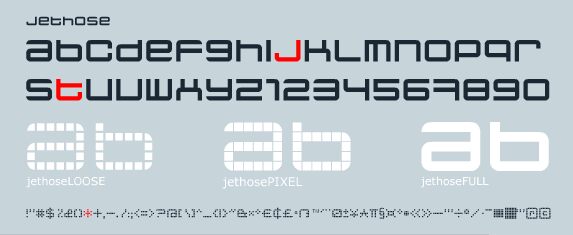
Jethose Full ist eine kostenlose, futuristische Display-Schrift mit einem markanten modularen Charakter. Sie besteht aus weichen, quadratischen Kurven und konsistenten Strichstärken und erinnert an Buchstaben, die aus glänzendem Kunststoff geformt oder als Leuchtröhren gestaltet sind. Die großzügigen Punzen und der straffe Rhythmus verleihen ihr eine klare, technisch präzise Anmutung, die schnell lesbar ist und gleichzeitig unverkennbar digital wirkt.
Mit Jethose Full verleihst du Sci-Fi-Postern, Logos für Tech-Startups, Spieletiteln, Covern für elektronische Musik und Veranstaltungsflyern einen schlanken, futuristischen Look. Diese kostenlose Schrift glänzt vor allem in großen Größen, wo ihre quadratischen Formen und präzisen Verbindungen besonders gut zur Geltung kommen. Für längere Fließtexte empfiehlt es sich, sie mit einer schlichten geometrischen Sans-Serif zu kombinieren, um das Layout ausgewogen und lesbar zu halten.